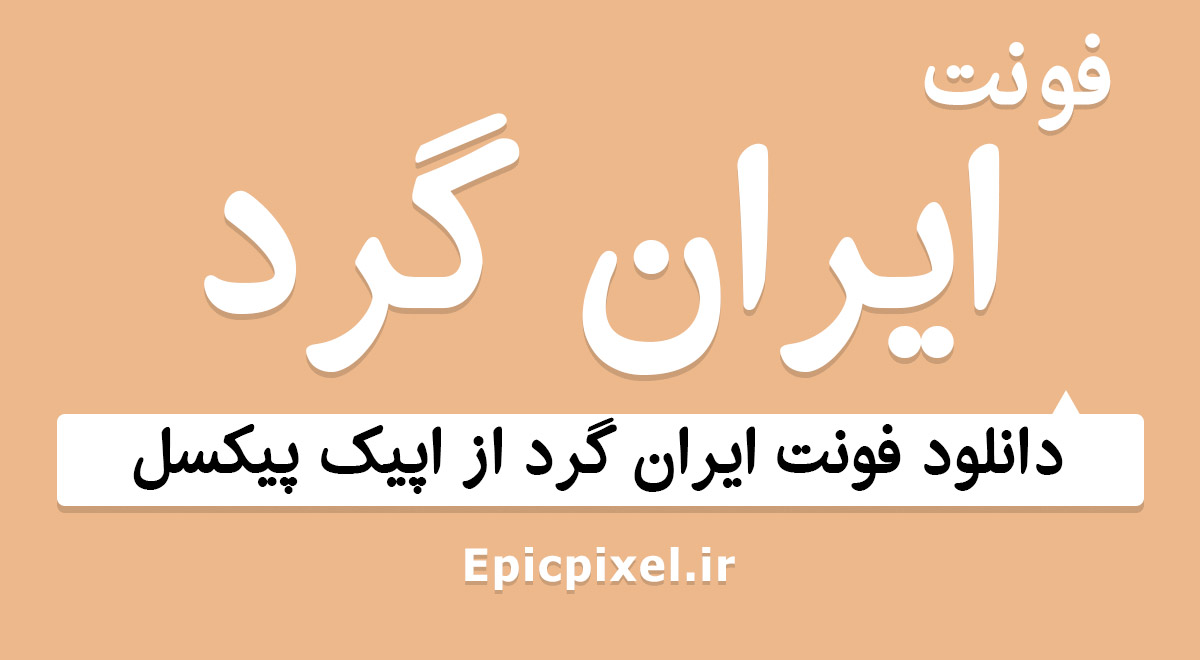
فونت ایران گرد فارسی
فونت ایران گرد، یه انتخاب عالی برای کساییه که دنبال یه فونت فارسی مدرن و در عین حال صمیمی می گردن. این فونت، در واقع یه نسخه بولد و نرم شده از فونت محبوب ایرانه که با گرد کردن گوشه های تیز حروف، ظاهری دوستانه تر و غیررسمی تر پیدا کرده. همین ویژگی باعث میشه نوشته هاتون حس و حال خودمونی تری داشته باشه و برای طراحی هایی که نیاز به یه فونت شیک و در عین حال راحت دارن، بی نظیر باشه.
یکی از ویژگی های برجسته این فونت، دایره ای بودن نقطه هاست که به جذابیت و فانتزی بودنش اضافه می کنه. تصور کنید نوشته هاتون با نقطه های گرد و دوست داشتنی چقدر می تونن چشم نواز باشن! این فونت به خوبی تونسته ساختار اصیل نسخ رو حفظ کنه و در عین حال، یه ظاهر مدرن و امروزی به خودش بگیره. به همین دلیل، هم برای متن های کوتاه و هم برای متن های طولانی، خوانایی بالایی داره و چشم رو خسته نمی کنه.